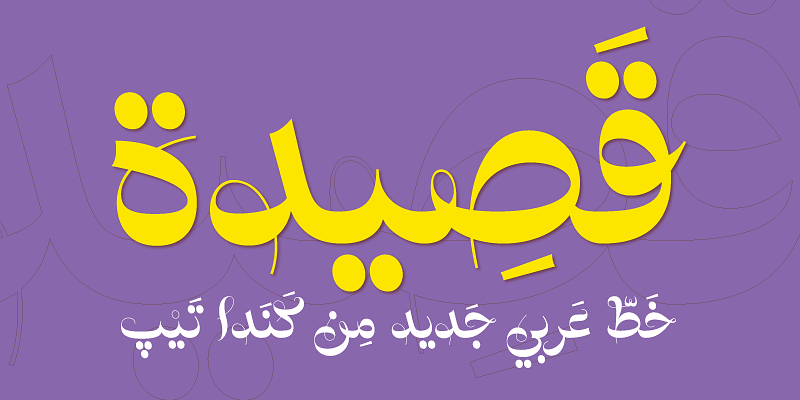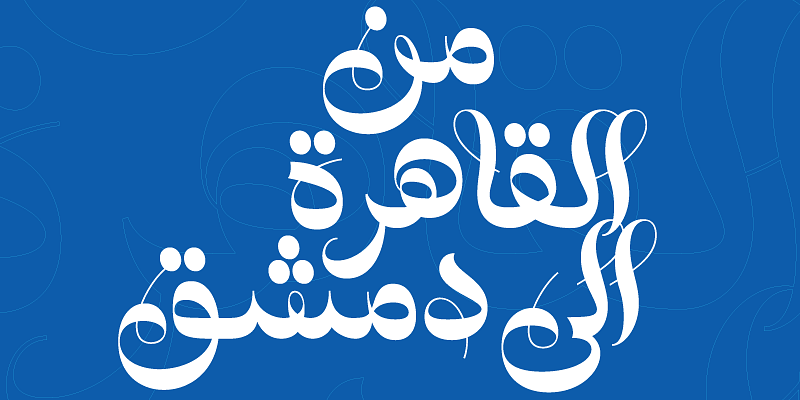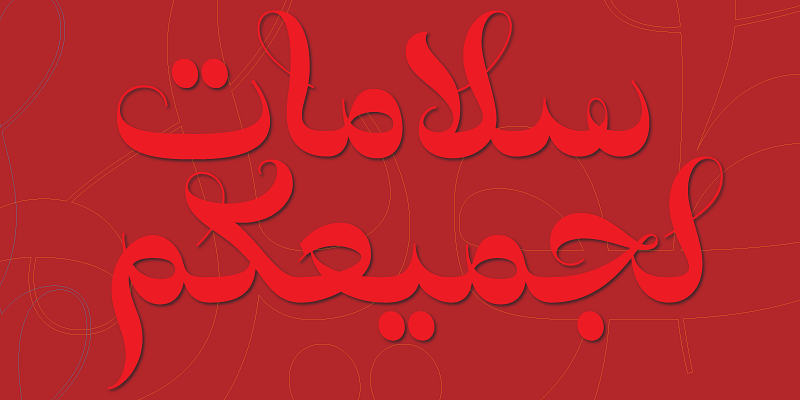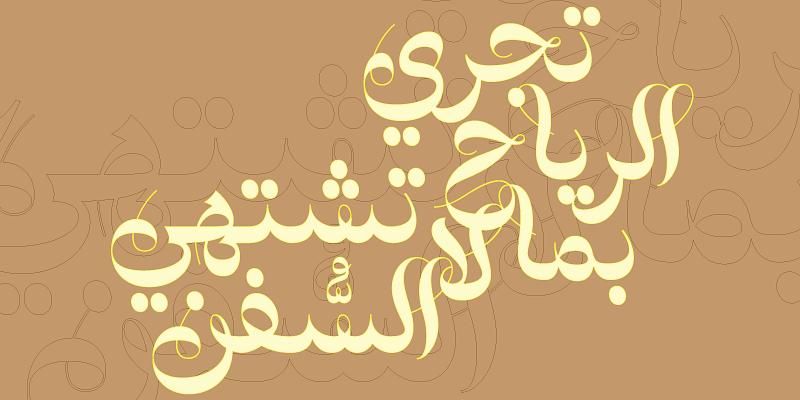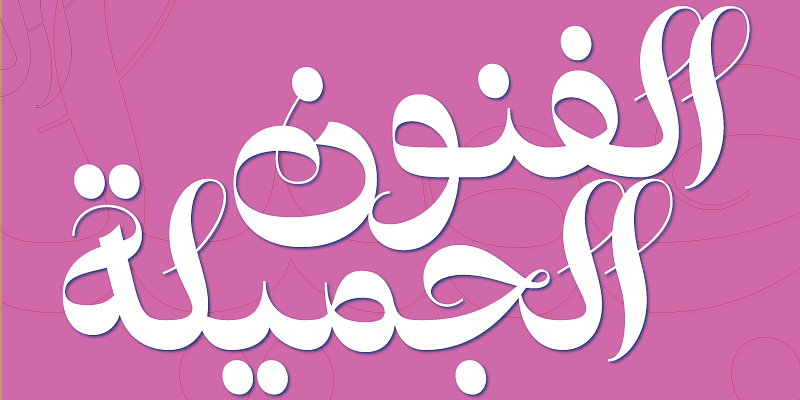
Qasida ist wild, ungebunden und voller Wunder, eine vollendete Darstellung des Ruq’ah-Stils, wie er von klassischen Programmzetteln, Buchumschlägen und Filmtiteln bekannt ist. Verwenden Sie sie zusammen mit stark kontrastierenden lateinischen Schriften.